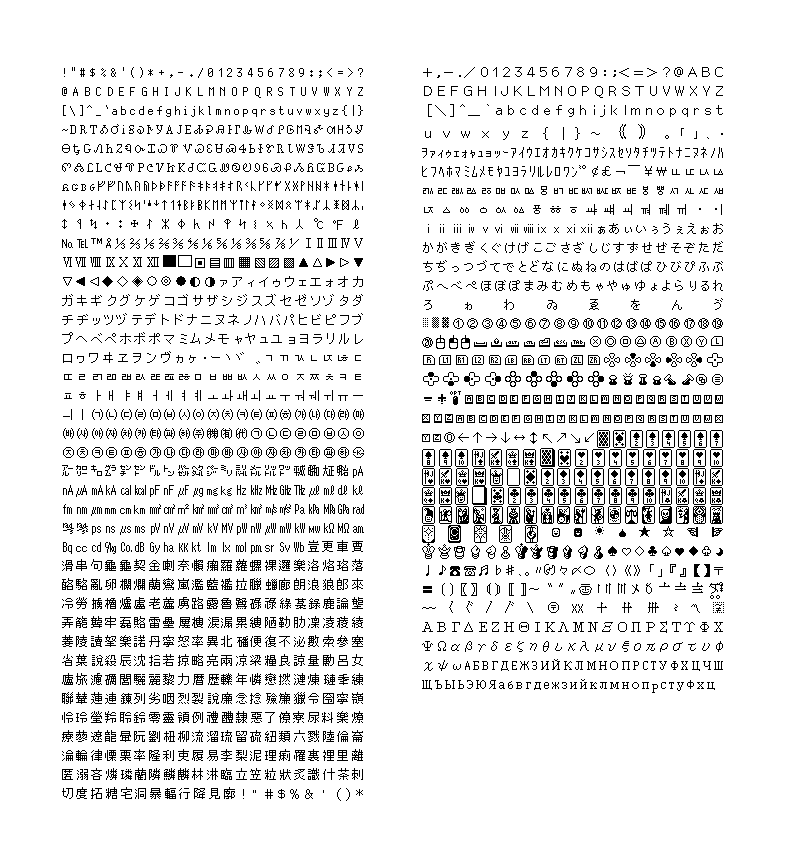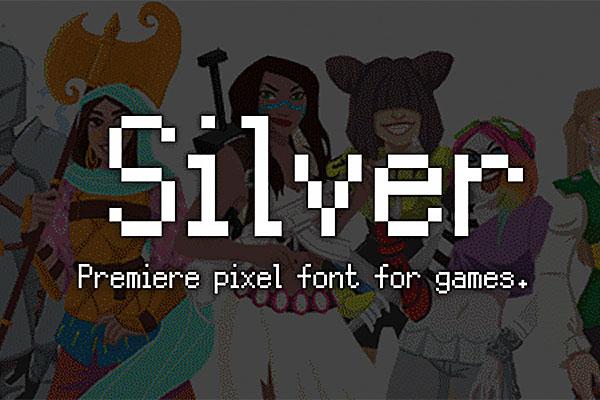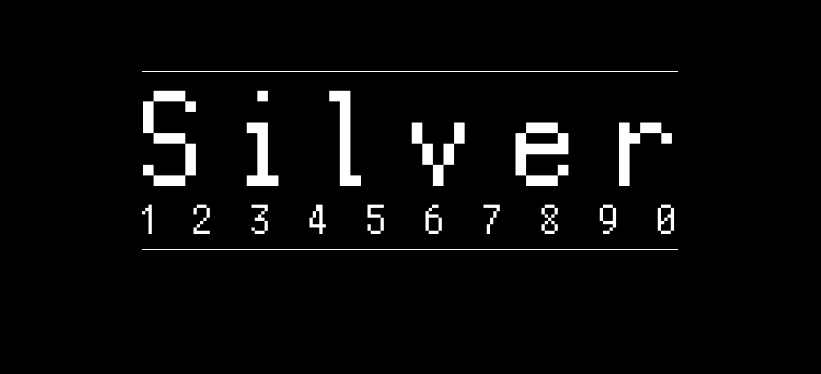
Silver
Silver字体介绍
Silver是一款专业的游戏用像素字体,该字体的作者是Poppy Works和Wolfgang Wozniak。像素字体没有半个像素这样的虚笔画,看起来清晰锐利,很有电子游戏的代入感。Silver虽然自由君将Silver归类为英文字体,但其实该字体是支持中文、日文等语言的字符的,在下面的示例部分就展示了部分字符,这款字体的官网在国外,链接非常不稳定,自由君反复尝试花费了4个小时才成功下载,喜欢的不要错过哦!
Silver字体应用示例